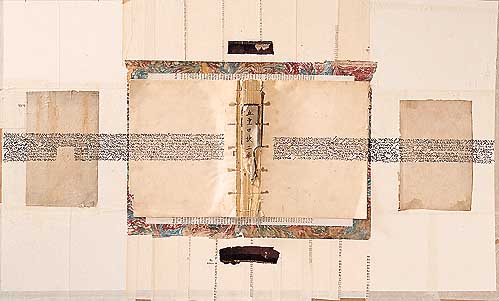
| The Book of Silence 1996 Text from "the Pillow Book" Collage of rice paper and old papers with ink, gouache, silver leaf, whitewash; 53 x 76 cm | |||||
| PRIMO PREMIO A BRODY NEUENSCHWANDER per la ricchezza propositiva e vitale della sua ricerca che emerge da tutti i suoi lavori in cui un impianto geometrico controllato esalta la complessità e la varietà dei singoli elementi compositivi. Le sue opere riservano sempre il piacere della scoperta rivelandosi provocatorie e schive allo stesso tempo, una sorta di coincidenza degli opposti: sono infatti assolutamente nuove ed inedite, ma percorse dal ricordo e dalla nostalgia per l'antico; mostrano una calligrafia che non abdica alla sua vocazione di essere veicolo di contenuti testuali, ma che è anche ricerca visiva indipendente dal testo che comunica; espongono una scrittura piena di naturalezza e di ritmo, ma rivelano allo stesso tempo che si tratta del frutto di un'esercizio e di una ricerca controllata in tutte le sue fasi; contrappongono la tessitura grezza di materiali diversi alla tessitura ritmata del fluire calligrafico; colpiscono immediatamente per il loro essere diversi, ma tutto lo spessore di questa diversità si rivela a poco a poco. | |||||